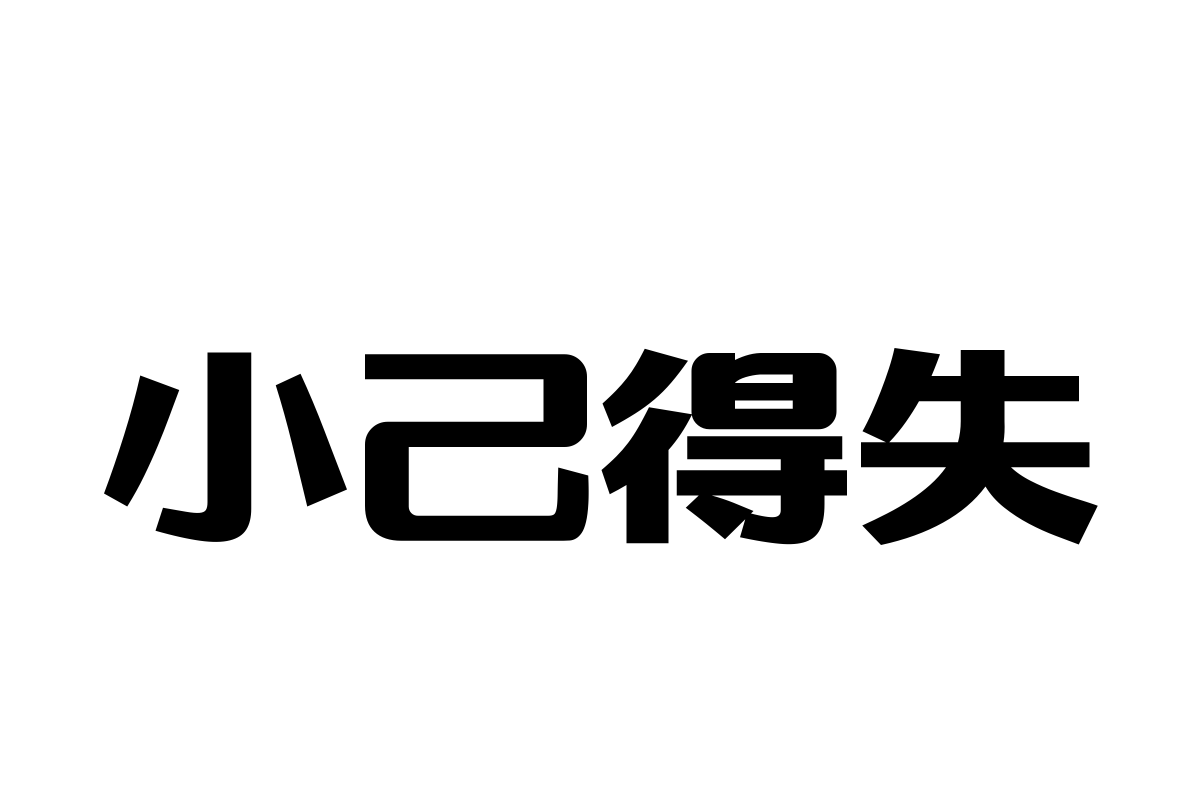
汉仪晓波敦黑是一款现代中文字体,由汉仪字库出品。这款字体具有独特的设计风格和特点,适合用于需要强调个性和创意的场合。
该字体采用了简洁明了的设计,线条流畅自然,整体给人一种轻松愉悦的感觉。同时,字体结构紧凑,笔画粗细适中,既适合正式场合使用,又能够很好地传达出轻松、活泼的氛围。
此外,汉仪晓波敦黑还具有一定的艺术感,能够很好地与各种设计元素相结合,为设计师提供丰富的灵感来源。无论是在平面设计、网页设计还是其他领域,这款字体都能够展现出其独特的魅力。